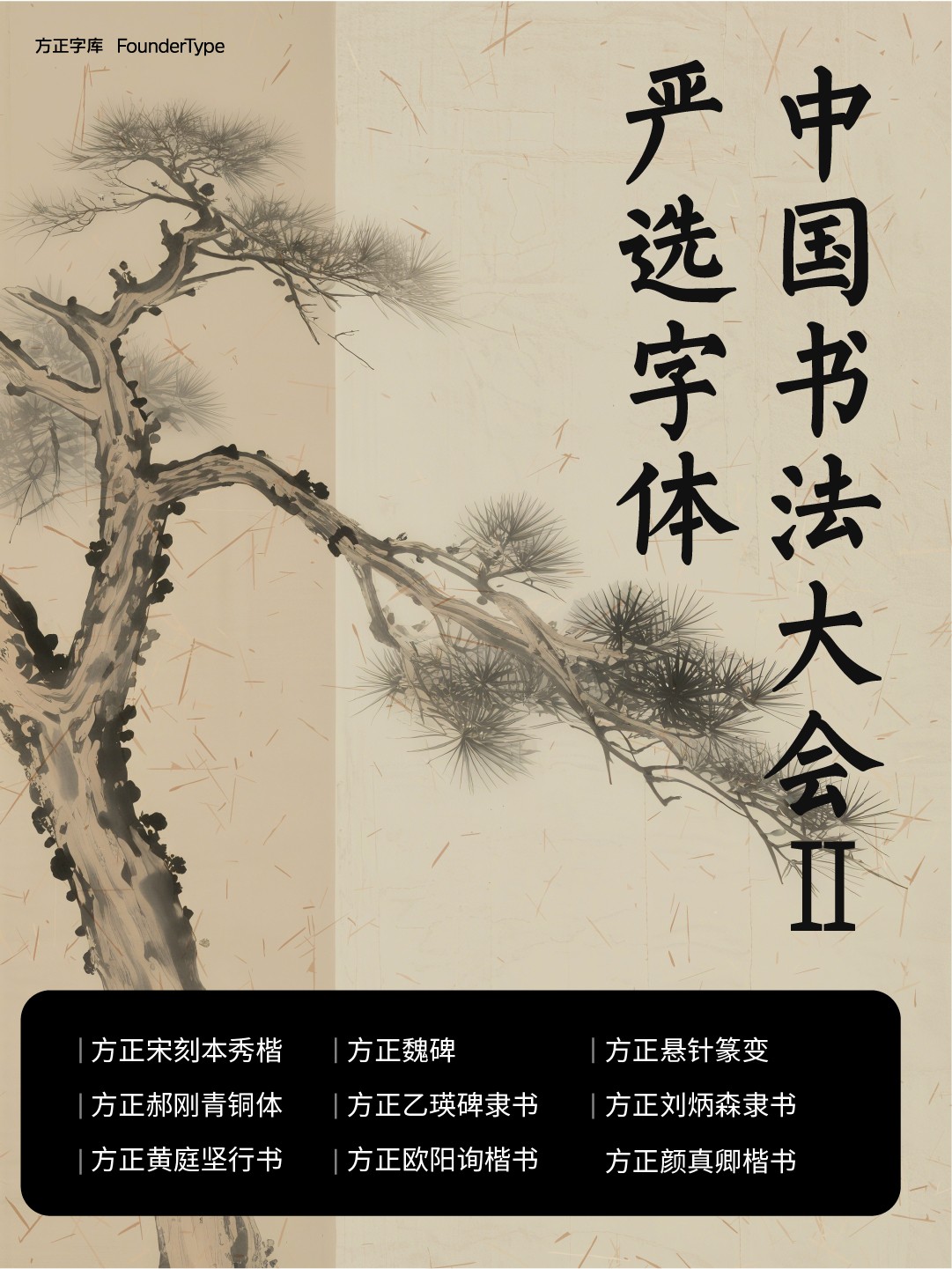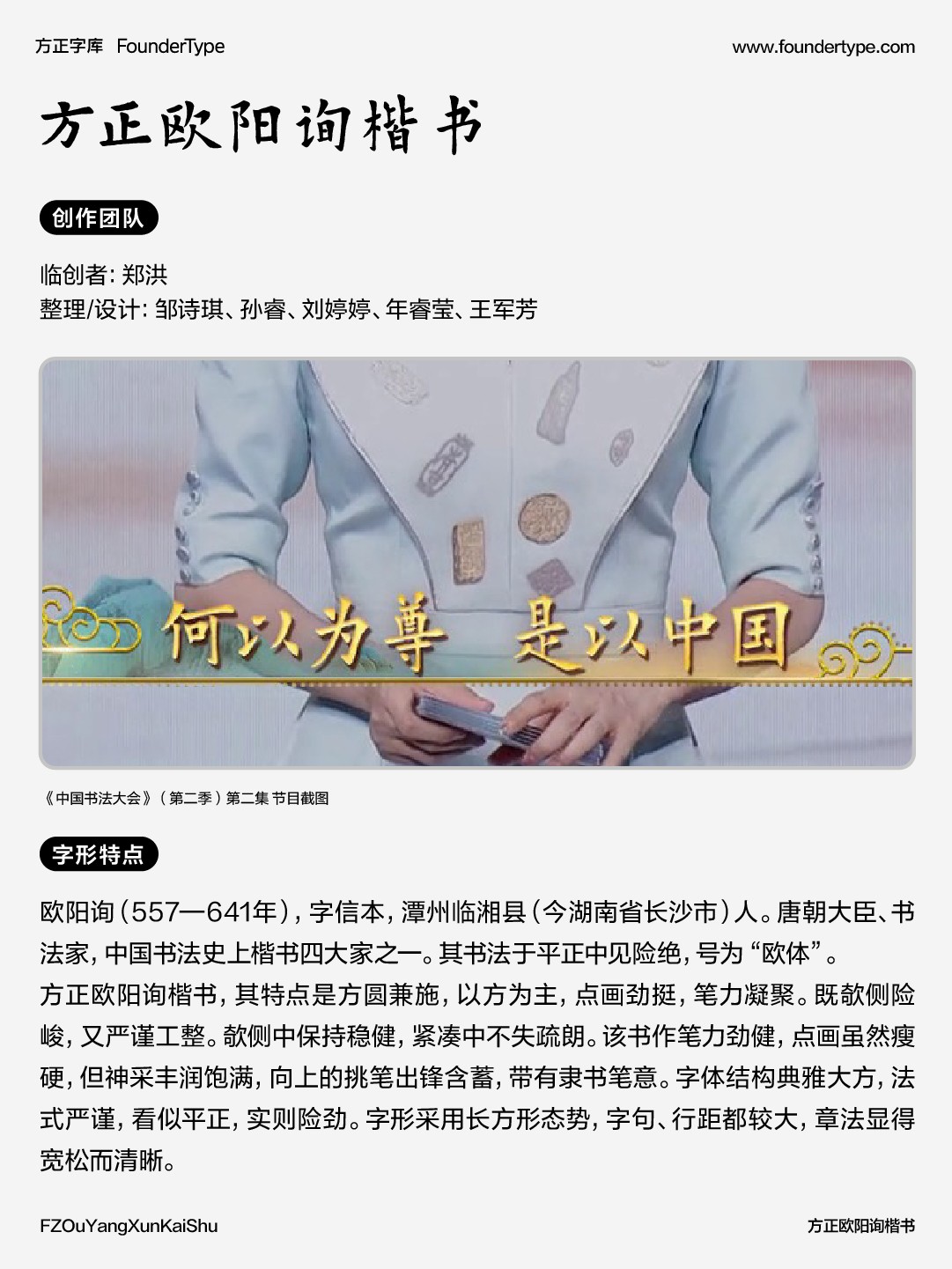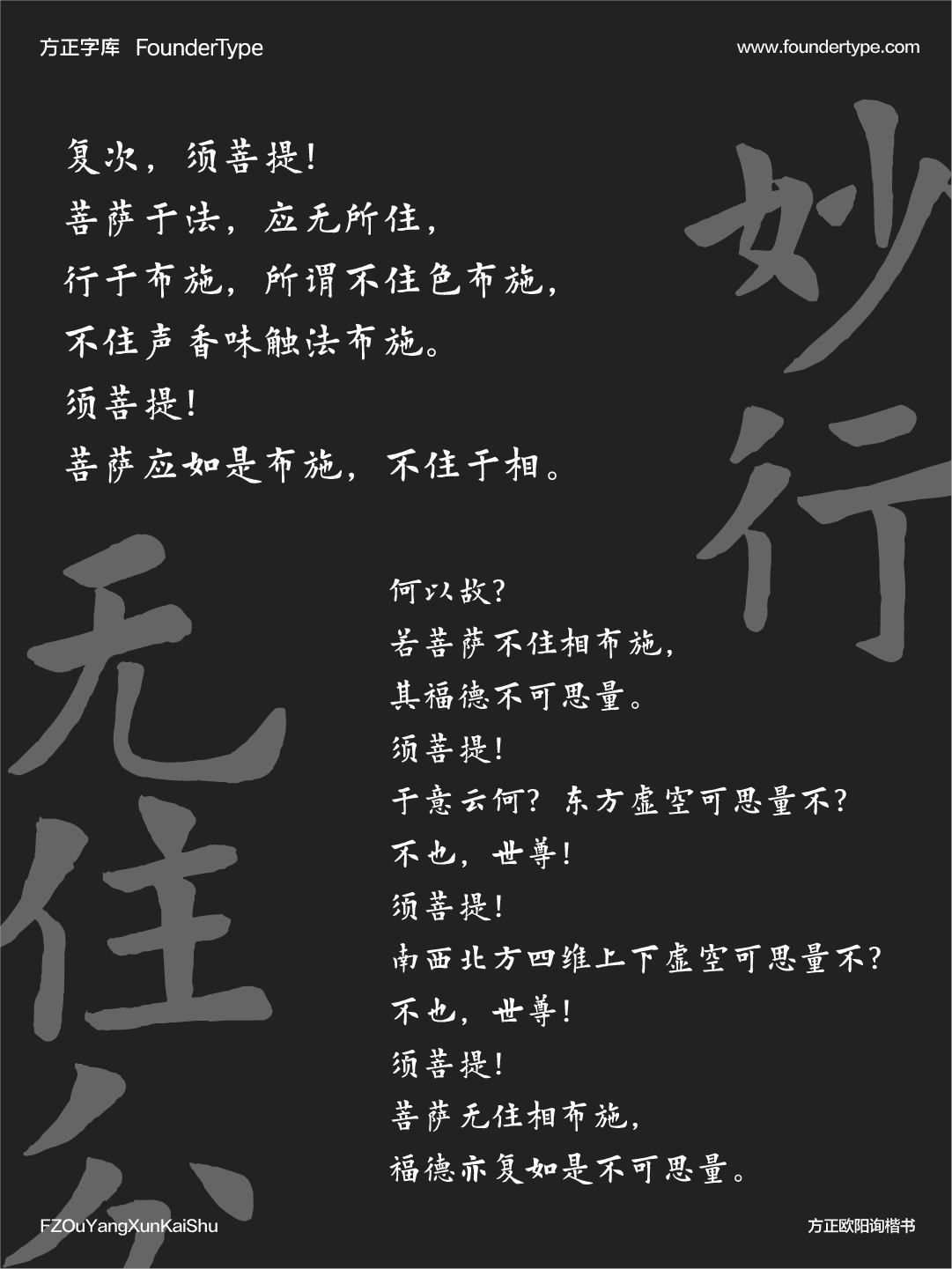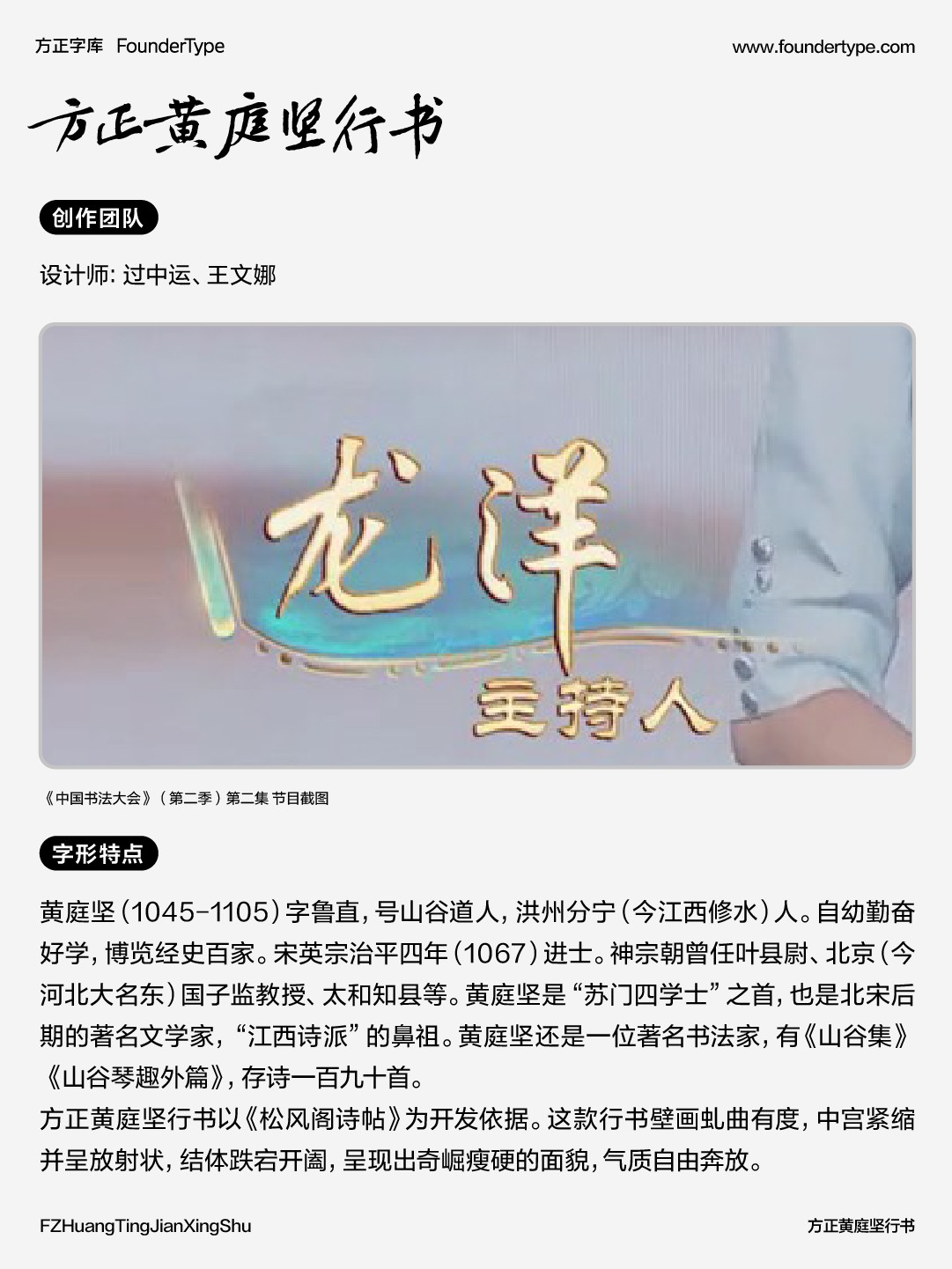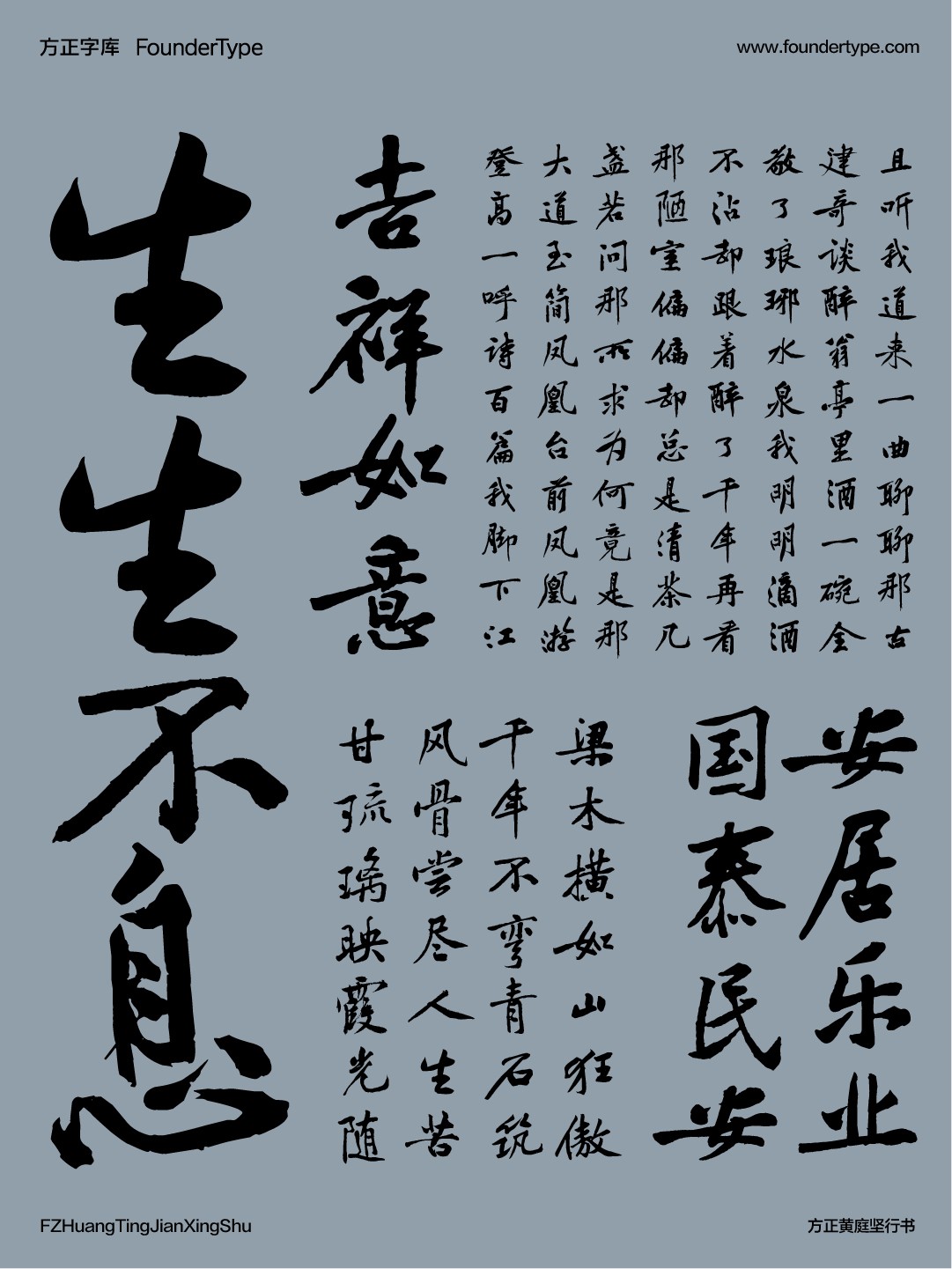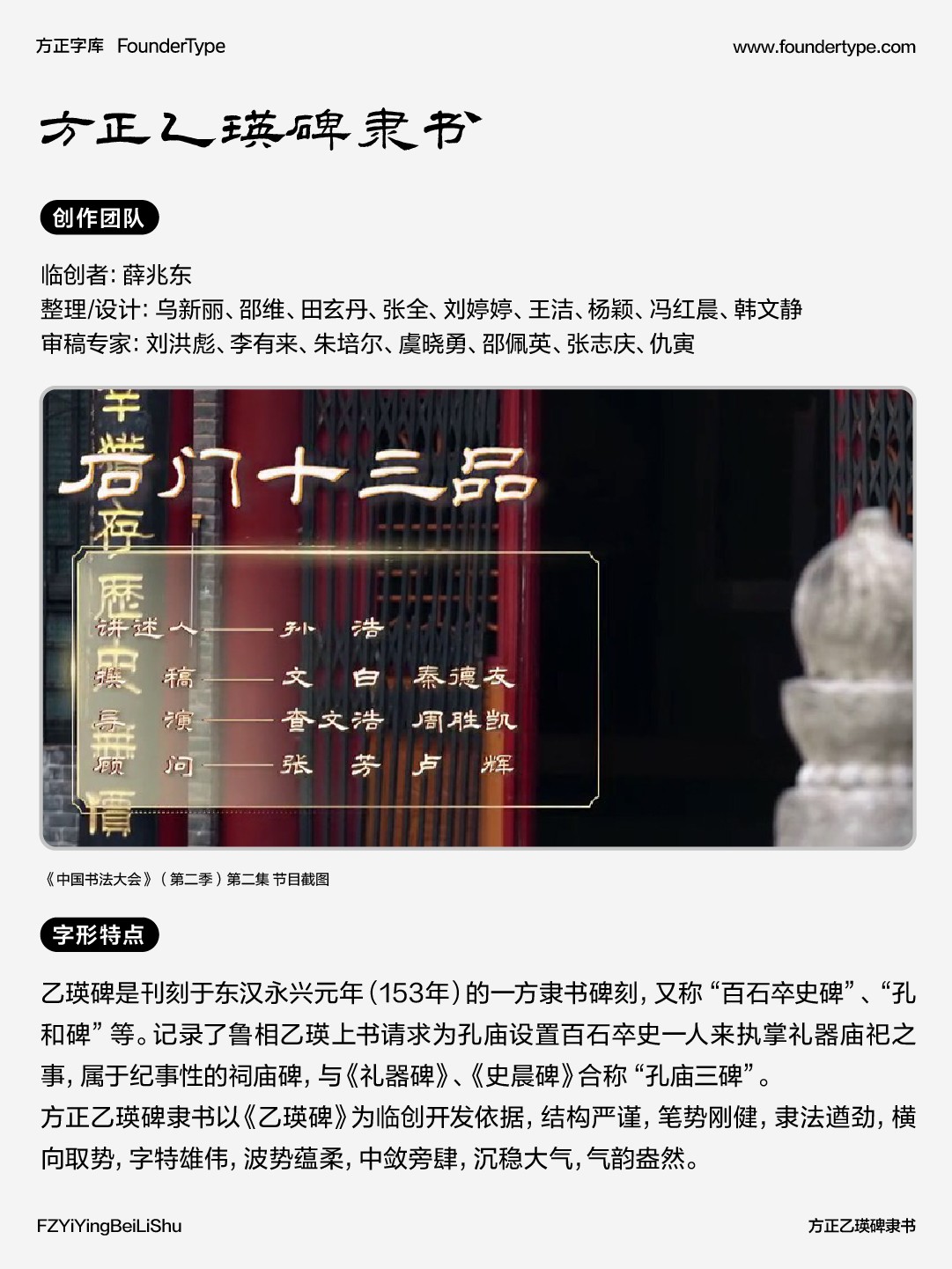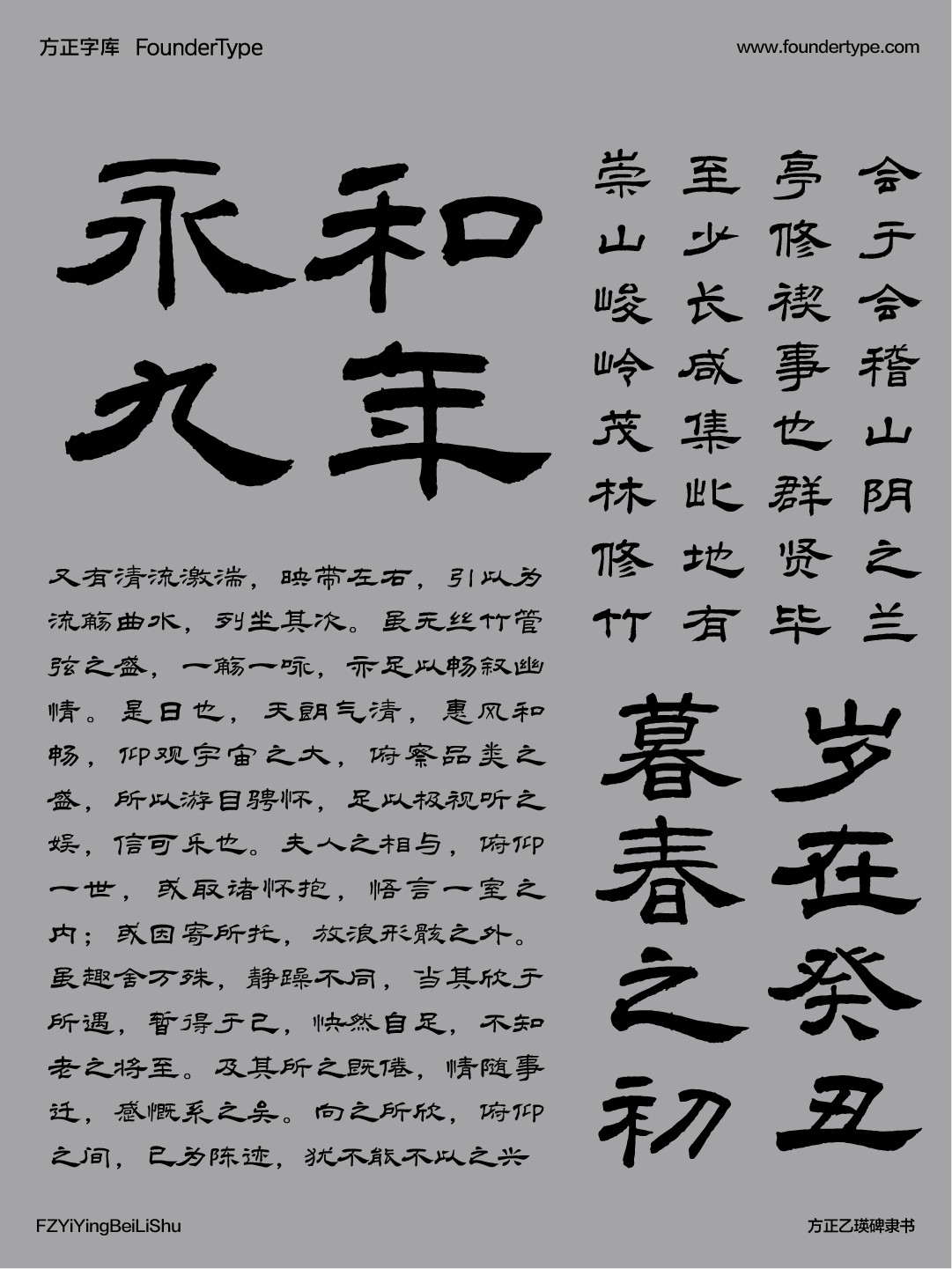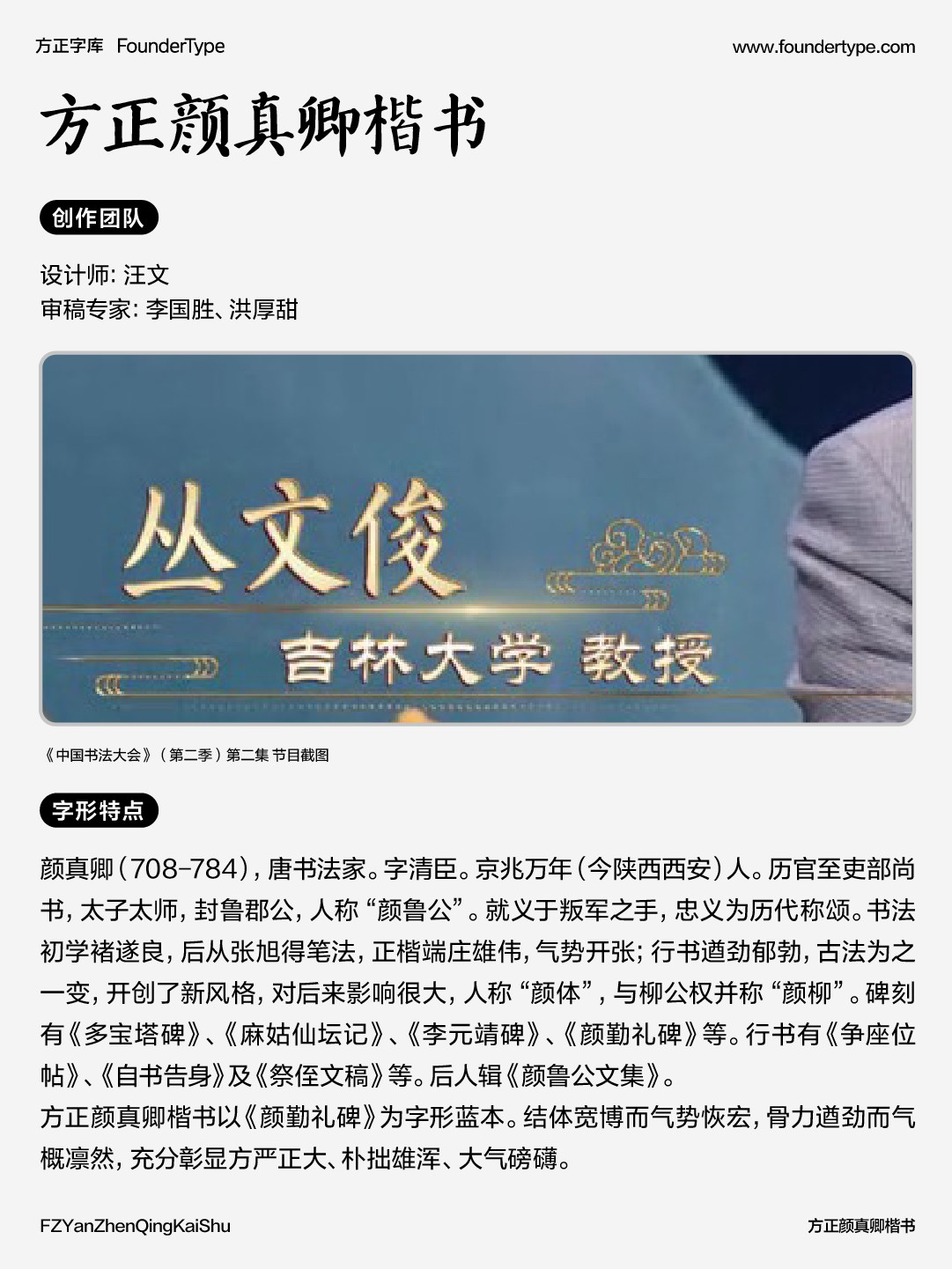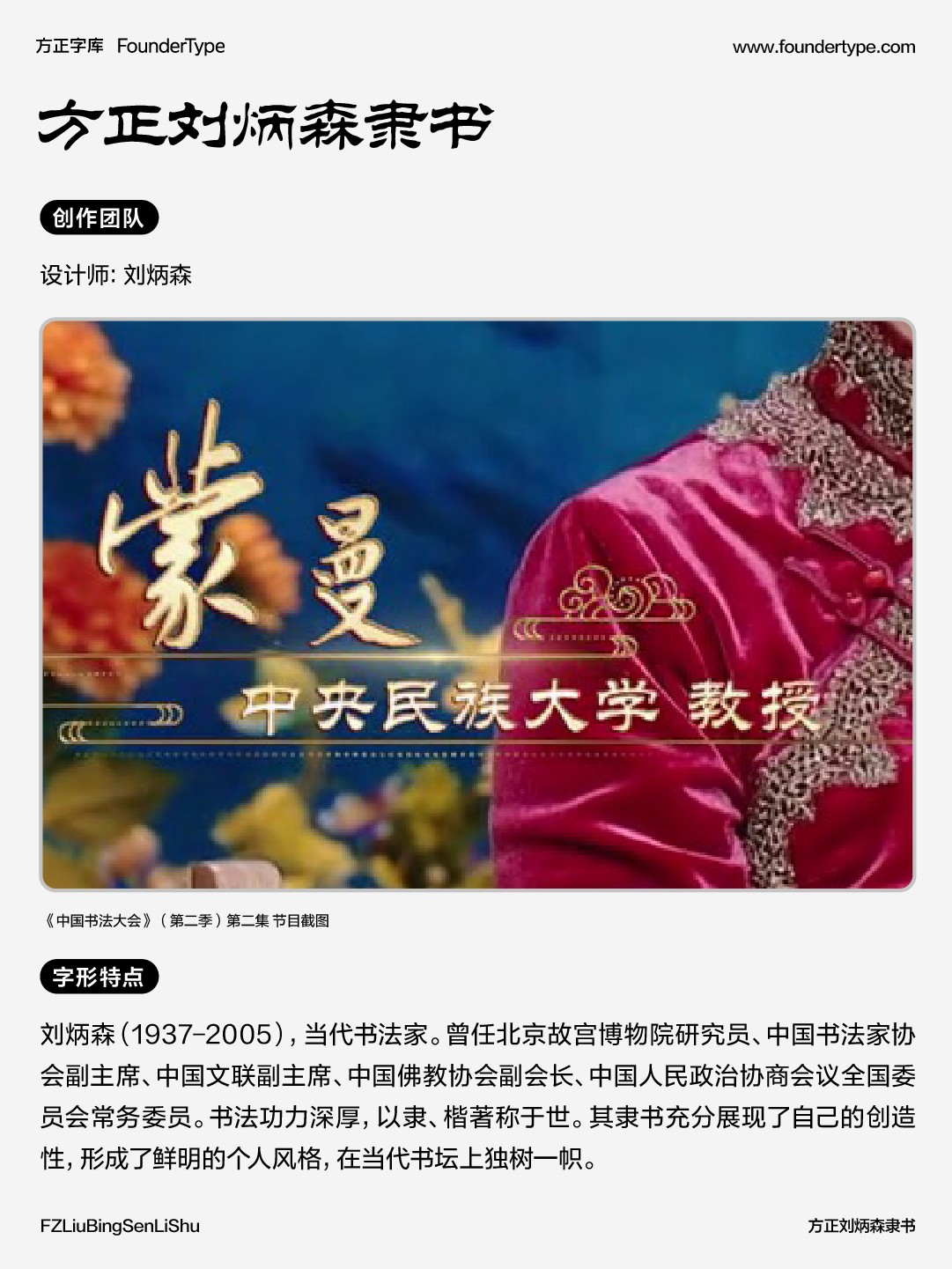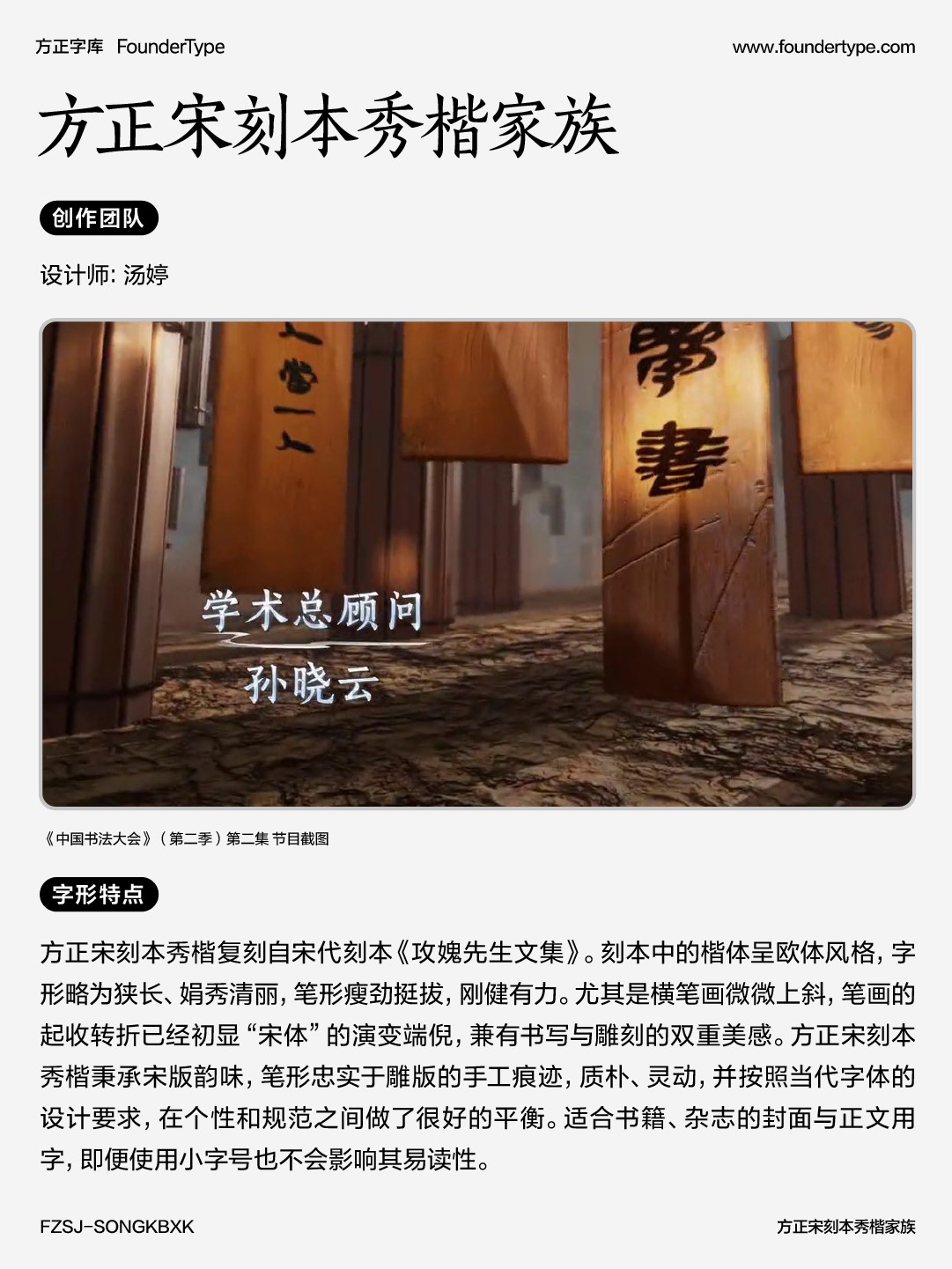
赏书法珍品,荐精品字体——聚焦《中国书法大会》第二季
6月20日,《中国书法大会》(第二季)第二集在CCTV-1重磅开播,央视频、央视网同步上线。本集聚焦周原遗址青铜器铭文、马王堆帛书与石门十三品等三组书法瑰宝,展现早期书法在甲骨、青铜、竹帛、山石等材质上的自然演变。
《中国书法大会》(第二季)在节目中全面采用方正字体,其中包括精品字体和中华精品字库工程优秀成果。中华精品字库工程是中华优秀传统文化传承发展工程支持项目,精选中国历代书法名家的代表作品开发成电脑字库,是对书法经典的数字化再创造。
节目中,数款方正字体被用作节目字幕或舞台动画元素,为画面呈现增光添彩,与各专家队伍智库、精彩节目内容共同形成有机的整体。方正字库以精品字体助力节目制作,通过视觉呈现的方式,生动讲好中国书法艺术故事,让书法艺术活起来、动起来,向世界传播中国优秀传统文化。
本期内容特别推荐第二集节目中出现的方正字体,邀您共赏书法艺术与现代字库的融合之美。